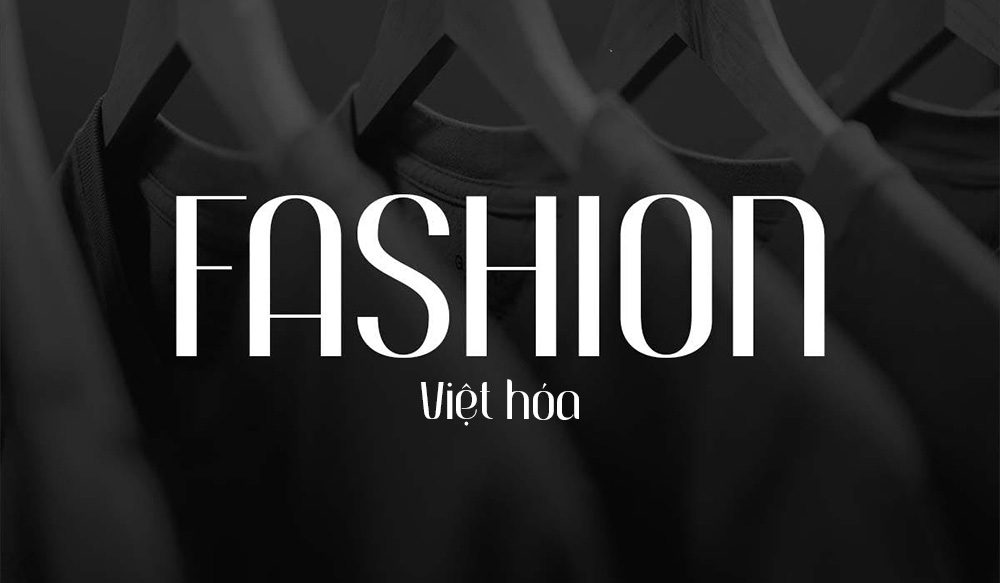
Font chữ thời trang Việt hóa là nhóm phông chữ được tinh chỉnh để thể hiện sự thanh lịch, đẳng cấp và tính thẩm mỹ cao, thường thấy trong các bản thiết kế của những thương hiệu hàng đầu thế giới. Đặc trưng của nhóm font này là sự kết hợp hoàn hảo giữa những nét thanh đậm tương phản mạnh mẽ hoặc cấu trúc tối giản đầy hiện đại. Doozypack.vn chia sẻ link tải font thời trang Việt hóa chuẩn, hỗ trợ đầy đủ tiếng Việt giúp bạn tự tin sáng tạo bao bì, nhãn mác và bộ nhận diện thương hiệu fashion ấn tượng.
Tại sao font chữ thời trang lại quan trọng trong thiết kế bao bì cao cấp?
Trong ngành công nghiệp sáng tạo, font chữ không chỉ để đọc mà còn là công cụ định vị giá trị sản phẩm trong tâm trí khách hàng.
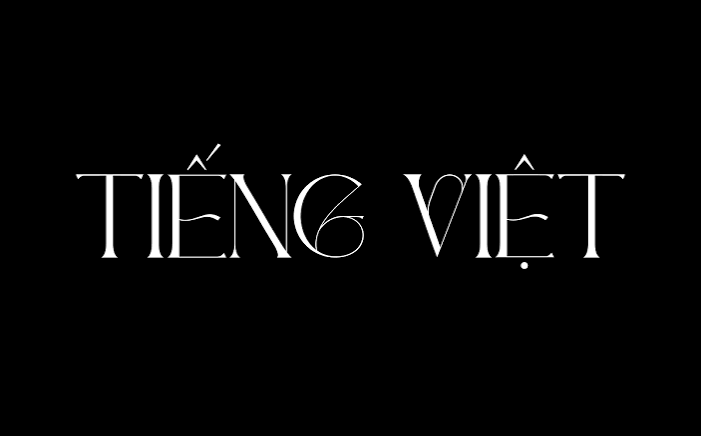
Khẳng định phong cách và cá tính riêng biệt của thương hiệu
Mỗi bộ font thời trang đều mang một “ngôn ngữ” riêng. Một font chữ có chân (Serif) với nét thanh mảnh gợi lên sự sang trọng cổ điển, trong khi một font không chân (Sans-serif) lại đại diện cho sự phóng khoáng và hiện đại. Việc sử dụng đúng phông chữ giúp thương hiệu thời trang truyền tải đúng cá tính, giúp khách hàng nhận diện shop của bạn giữa hàng ngàn đối thủ cạnh tranh.
Tạo ấn tượng về sự sang trọng và tính thẩm mỹ vượt trội
Các font thời trang chuyên dụng thường được thiết kế với tỷ lệ vàng, tạo nên sự cân đối tuyệt đối về thị giác. Khi được in trên các chất liệu cao cấp, phông chữ này giúp bao bì sản phẩm trông “đắt tiền” và chỉn chu hơn. Đây là yếu tố quan trọng để nâng cao trải nghiệm mua sắm và tạo niềm tin về chất lượng sản phẩm đối với khách hàng.
Top bộ font thời trang Việt hóa kinh điển được Designer tin dùng
Dưới đây là một số gợi ý font thời trang việt hóa hàng đầu, phù hợp cho mọi nhu cầu thiết kế in ấn:
- Font Playfair Display: Sở hữu nét thanh đậm rõ rệt, cực kỳ phù hợp cho các tiêu đề tạp chí, bìa lookbook hoặc in hộp quà tặng sang trọng.
- Font Bodoni / Didot: Những bộ font “huyền thoại” gắn liền với phong cách Didone, là biểu tượng của sự quý phái và đẳng cấp trong ngành thời trang cao cấp.
- Font Montserrat: Phông chữ Sans-serif hiện đại, sạch sẽ, được các local brand vô cùng ưa chuộng nhờ tính đa dụng và vẻ đẹp tối giản.
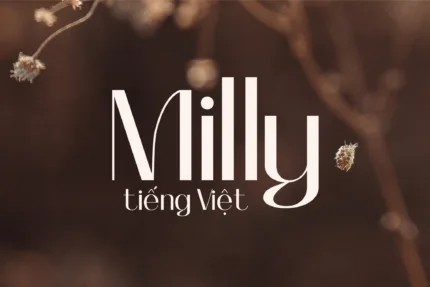
| Phong cách Font | Đặc điểm thị giác | Ứng dụng in ấn phù hợp |
| High-Contrast Serif | Thanh mảnh, quý phái | In hộp cứng cao cấp, thiệp mời sự kiện thời trang, logo nước hoa. |
| Minimalist Sans | Hiện đại, gọn gàng | Túi giấy shop quần áo, tem nhãn mác áo, túi vải canvas. |
| Elegant Script | Bay bổng, cá tính | Thiệp cảm ơn, túi giấy quà tặng, decal dán hộp sản phẩm handmade. |
Tư vấn từ xưởng in: Khi sử dụng các font có nét thanh đậm mạnh như Bodoni, bạn cần lưu ý đến độ mảnh của nét chữ. Trong in ấn thực tế, các nét siêu mảnh (hairline) có thể bị mờ hoặc đứt nét nếu in trên chất liệu giấy quá nhám. Hãy tăng nhẹ độ dày nét (Stroke) nếu cần thiết để đảm bảo độ sắc nét.
- Hộp giấy cao cấp: Các dòng hộp cứng đựng giày, ví hay trang sức sẽ trở nên đẳng cấp hơn khi kết hợp font thời trang với các kỹ thuật gia công bề mặt.
- Thẻ treo và thiệp cảm ơn: Những chi tiết nhỏ như tag mác áo được thiết kế bằng phông chữ thời trang chỉn chu là minh chứng rõ nhất cho sự tận tâm và chuyên nghiệp của thương hiệu đối với khách hàng.
03 Những lưu ý kỹ thuật khi in ấn font chữ thời trang nét mảnh
Việc đưa những thiết kế thời trang từ màn hình vào sản xuất thực tế đòi hỏi sự kiểm soát kỹ thuật nghiêm ngặt tại Doozypack.vn:
- Kỹ thuật ép kim (Foil Stamping): Font thời trang nét mảnh rất đẹp khi ép kim vàng hoặc bạc. Tuy nhiên, nếu nét chữ quá nhỏ, kim loại nóng có thể không bám đều hoặc làm lem chữ. Bạn nên tham khảo ý kiến kỹ thuật tại xưởng về kích thước chữ tối thiểu trước khi xuất file.
- Lựa chọn chất liệu giấy: Các phông chữ thời trang tinh tế thường đạt hiệu quả thẩm mỹ tốt nhất trên giấy Couche cán mờ hoặc các loại giấy mỹ thuật có bề mặt mịn, giúp làm nổi bật từng đường nét thanh thoát của chữ.